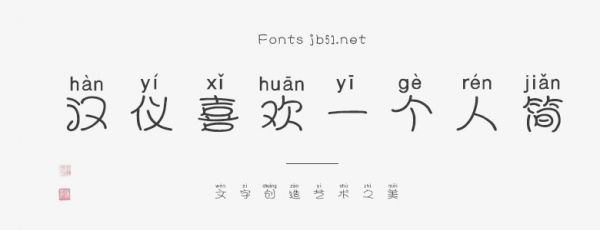
漢儀喜歡一個(gè)人簡(jiǎn)是由漢儀字庫(kù)出品,字體筆觸纖細(xì),字形圓潤(rùn),具有很好的視覺(jué)感,適合應(yīng)用于藝術(shù)設(shè)計(jì)、平面宣傳設(shè)計(jì)、網(wǎng)頁(yè)設(shè)計(jì),書法字帖等領(lǐng)域,需要的朋友可以前來(lái)本站下載。